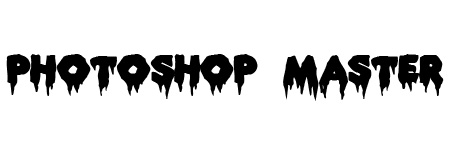
Шрифт - ROCKY
Необычный шрифт, который прекрасно подойдёт для работы в фотошоп. Без поддержки русского языка.
А с русскими буквами есть? Или хотя бы какой-то другой русский шрифт, похожий на этот?
Спасибо как будто только покрасили и краска потекла очень клева!!!
прикольный шрифт
можно делать для работ с кровью)
Nikola этот шрифт не без поддержки русского языка))А так клёвый шрифт))